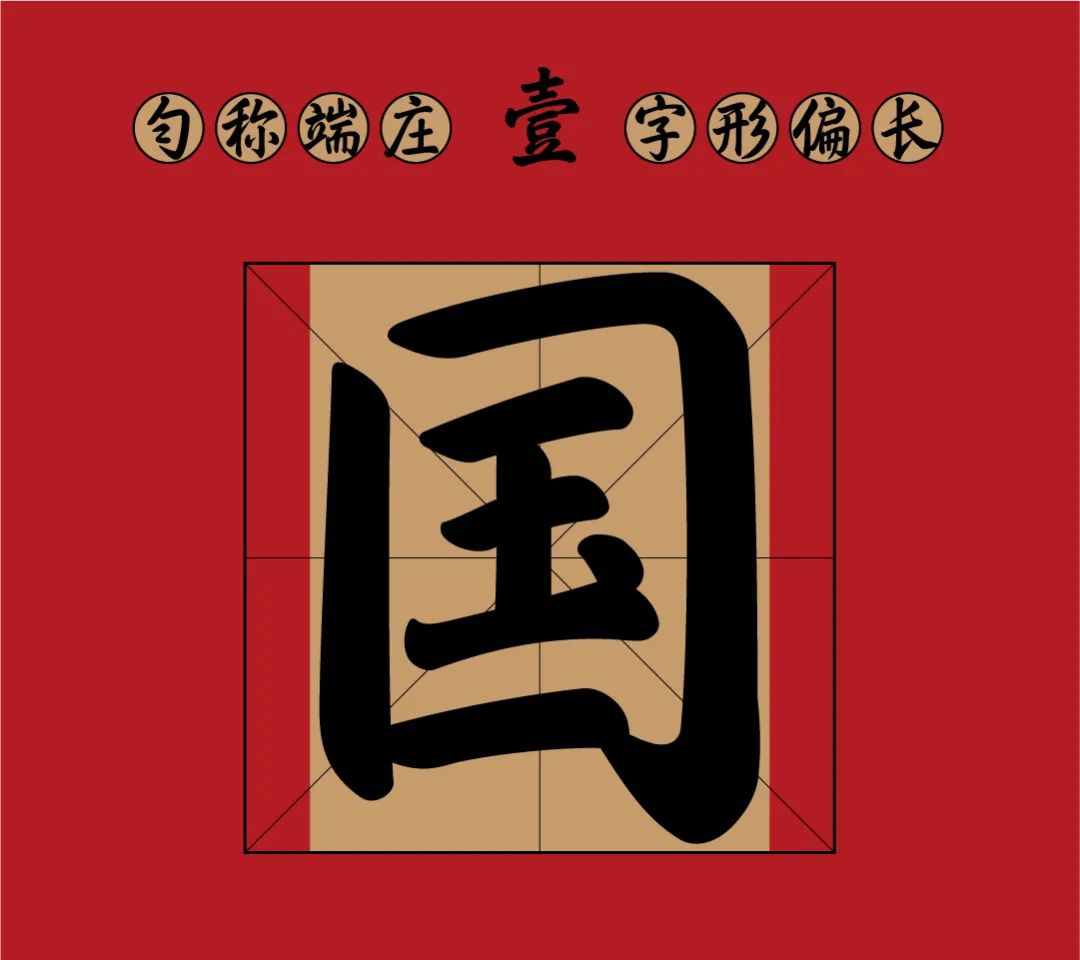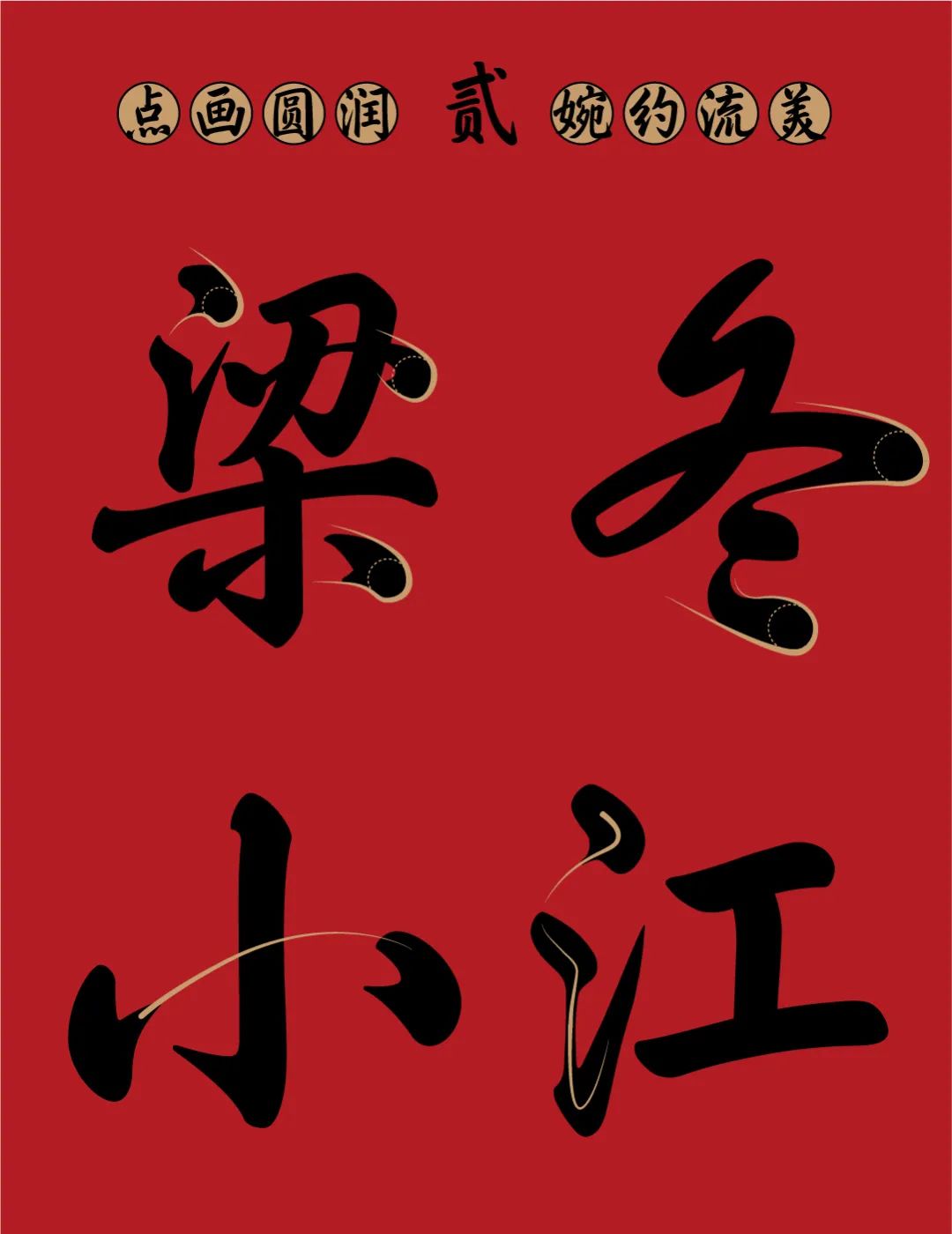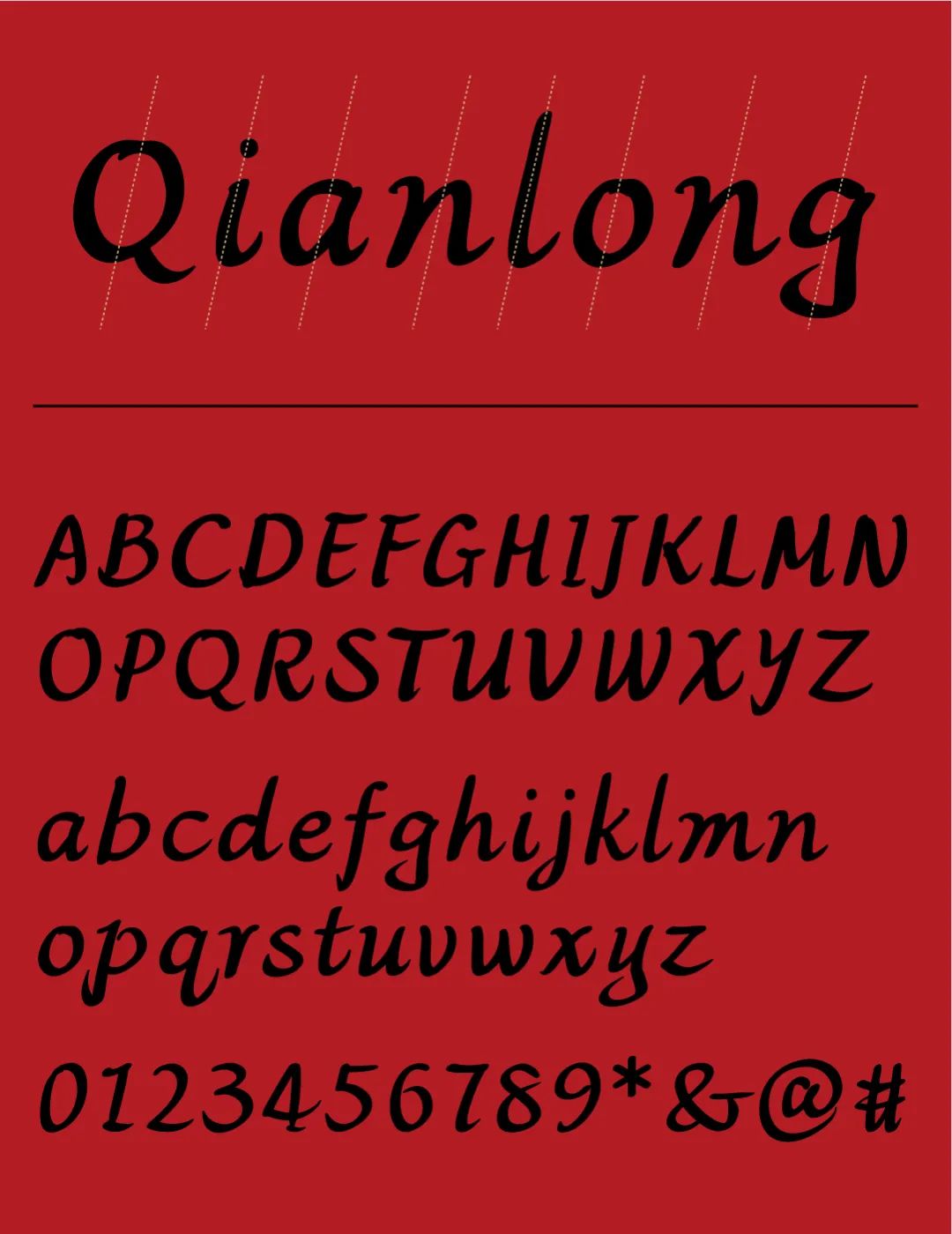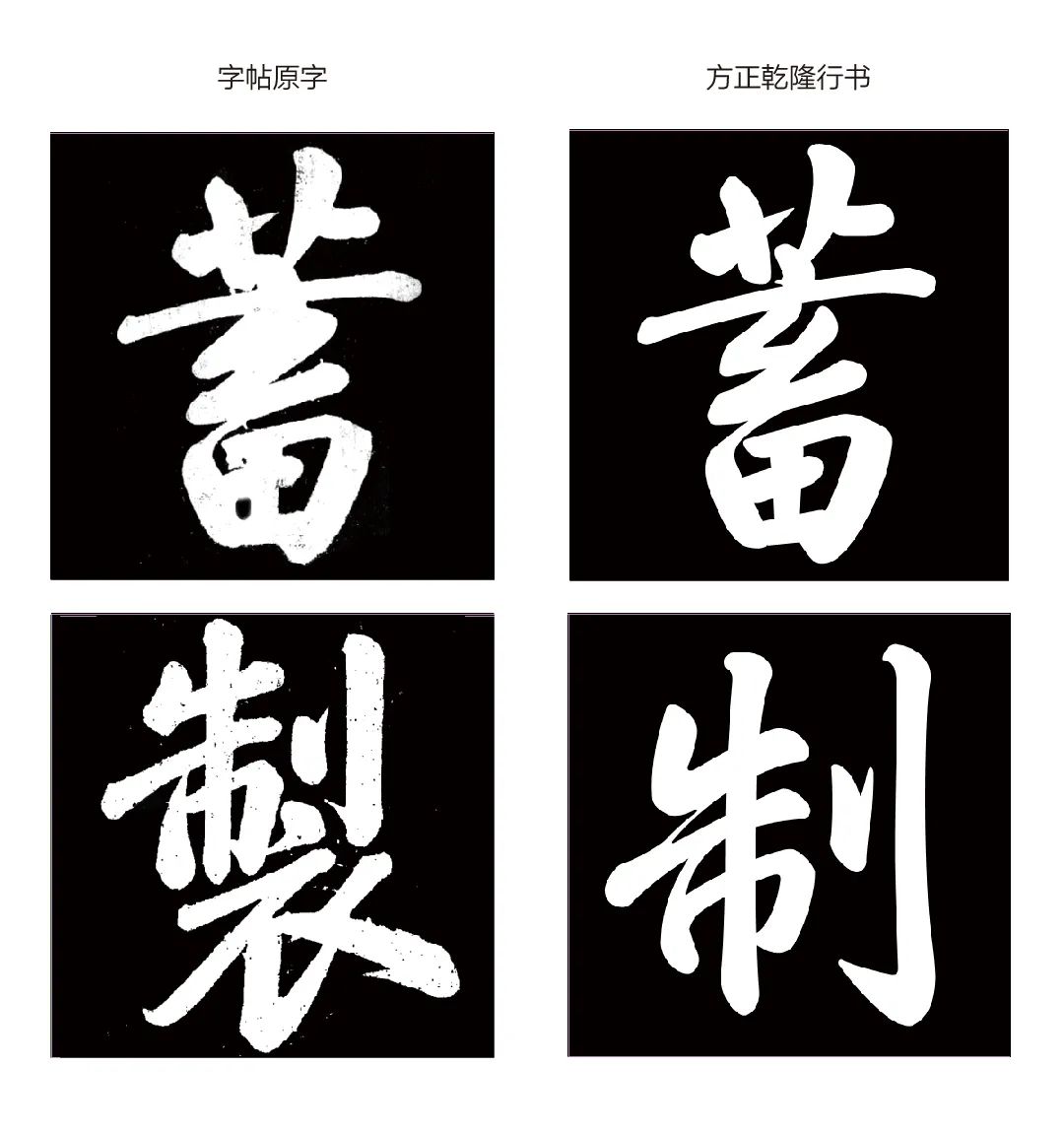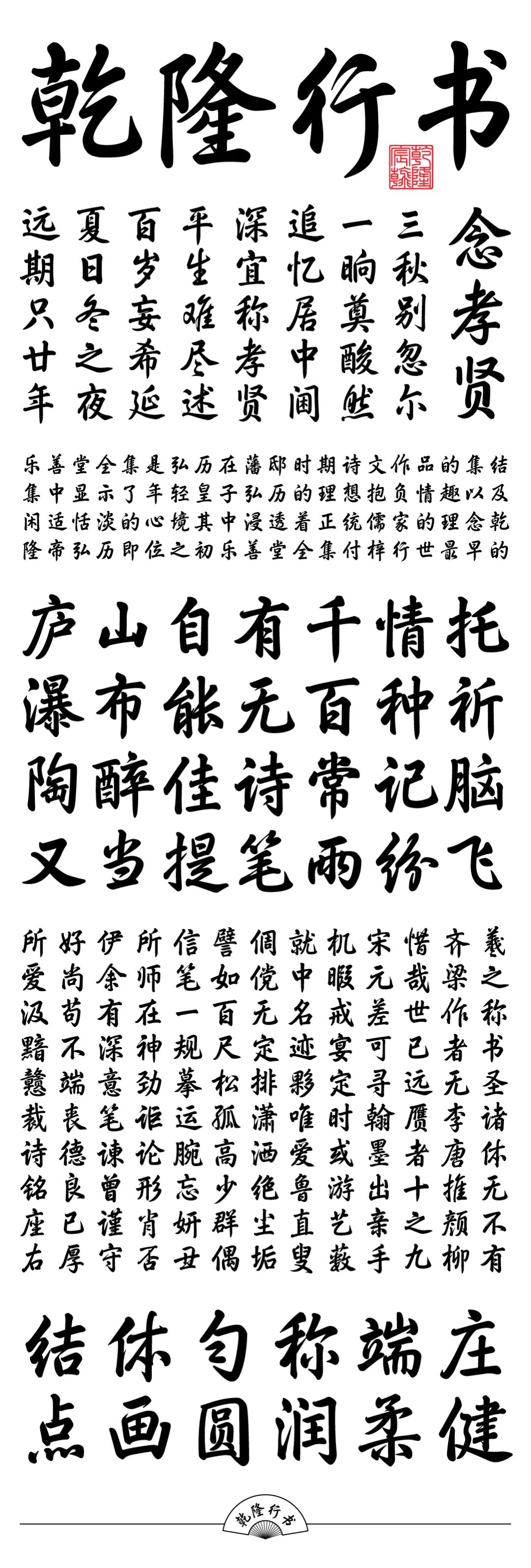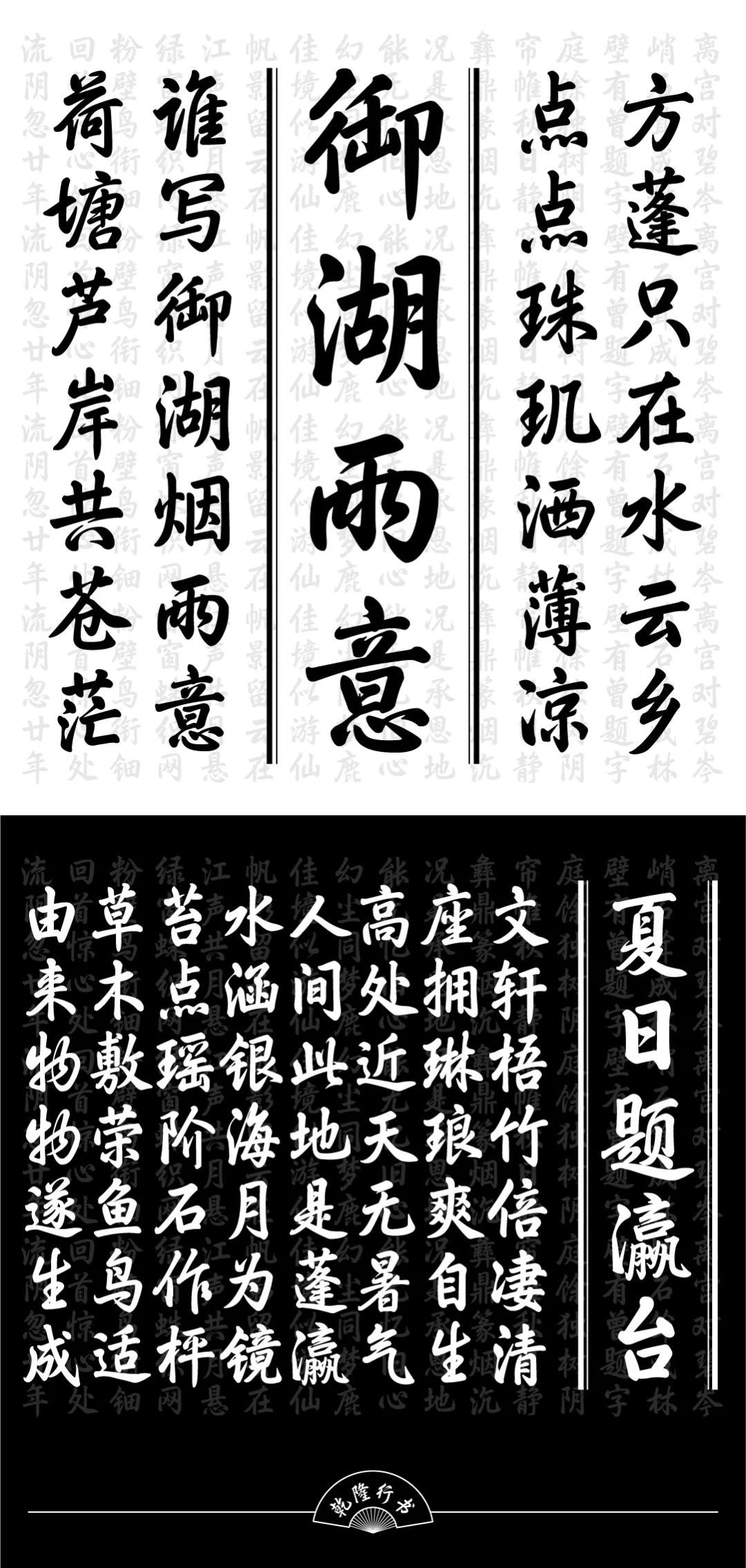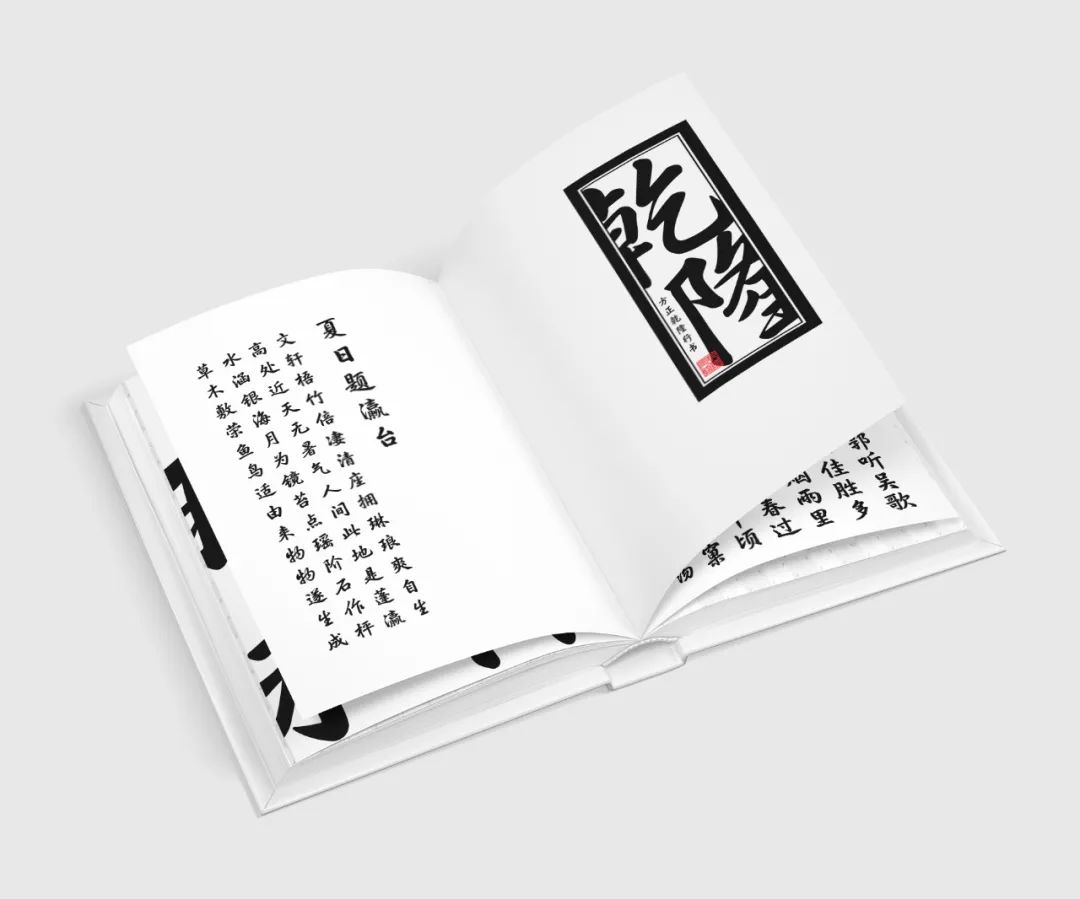
方正乾隆行书
乾隆的书法,圆润端庄而又遒丽,自带一股风雅气息。太平的乾隆时期,造就了这位帝王的字闲散而没有棱角。随便逛逛的名胜古迹就可以使我们忆起这位本该庄严的帝王发散出的可爱随性。方正在设计这款字库时,搜寻了大量字帖,拍摄了景区大量提字匾额,最后“乾隆万寿山昆明湖记书法”成为字库的首要素材。这款字帖,把乾隆帝最有特点的笔势和风格发挥的淋漓尽致。一横一竖,一撇一捺,把繁体转化成简体而风格不变,看似简单,实则艰难。历史长河,科学时代,古与今的碰撞,相辅相成!
乾隆,即清高宗(1711—1799),爱新觉罗·弘历,清代皇帝,1735-1795在位。乾隆自幼接受汉族文化传统教育,书法绘画无一不精,其作品字体稍长,圆润遒丽,结构婉转流畅,楷中有行,行中有草。作为一代帝王,乾隆书法还是有一定的特殊地位。此款乾隆行书,延续了乾隆书法的圆润与流畅,笔锋处适当硬朗, 使其圆润但有筋骨,特点更加鲜明生动。
方正乾隆行书设计开发团队
设计指导:仇寅,汪文
开发小组成员:林彤,杨颖,邵维,高茜,卫欢欢,刘晶,孙睿,田玄丹,关秋培,周佳敏
西文及符号设计:郭毓海
在中国古代书法史上,历代帝王书法扮演着重要的角色。痴迷于书法研究的帝王有很多,乾隆皇帝就是其中一位。
爱新觉罗·弘历(1711-1799),清代皇帝,世宗第四子,年号“乾隆”。在位六十年,留下书作千汇万状,有很高的书法、诗文造诣。经过一生对书法的练习研究,逐渐形成自己圆润端丽、温妍儒雅的书法风格。
乾隆帝的书法各体兼能,以行书见长。考察其传世书法,创作的时间长达六十多年,行书书法始终维持“端、润”的基本面貌。
《麦色诗》轴 清乾隆 故宫博物院藏
乾隆在中国历史长河中的地位不可忽视,他的字遍布大江南北,目前存世墨迹仅故宫博物院就藏有两千余幅。为了让书法爱好者近距离感受“乾隆体”,为社会各界应用乾隆字体提供实用上的便利,方正字库最新开发出「方正乾隆行书」字库。
「方正乾隆行书」字库的设计开发过程历时七年,从最初的字帖搜集、图片拍摄,到原字制作修改,开发团队不断钻研,经历了艰难的抉择。尤其是在字的筛选上,同一个字不同字型各有千秋,取舍不易。本着最大化还原乾隆书法风貌的原则,最终定位于乾隆行书,以“万寿山昆明湖记书法”为字库的主要开发依据,取其圆润流畅的风格进行创作。
乾隆的书法,圆润端庄而又遒丽,自带一股风雅气息。稳妥的结构,加上用笔上藏锋多于露锋,中锋多而侧锋少,才会使“乾隆体”的笔势致于中,达于和。这种有蕴藏的字经过时间的积累,也会变得愈发浓厚甘醇。
方正乾隆行书的西文与中文的风格和气质保持一致,字体稍长、笔形圆润,手写感十足。中西文搭配起来独具婉约美,富有亲和力。
古与今的灵感碰撞,在千百次的融合中归为一体。在一年半的创作时间里,最有挑战的是从简体到繁体的转变,一横一竖,一撇一捺,看似简单实则不易。不仅需要对笔画进行拆分,提取不同的部件,还需经多次实验的磨合,方可造就出符合时代审美的笔势形态。
林彤从事字体制作多年,完成字体产品数量多达几十种,参与过众多精品字的开发,培养新生力量后备军,经验丰富。是中华大字库工程制作负责人,可口可乐在乎体制作负责人,负责乾隆体创作等。